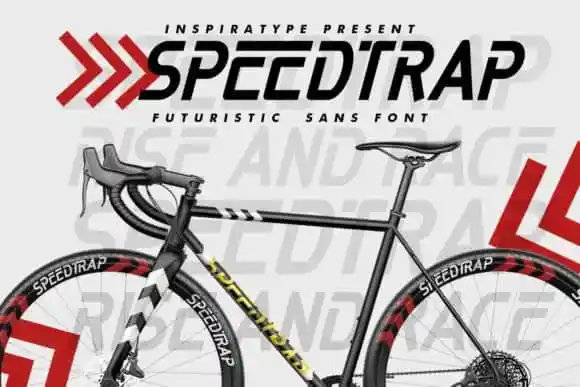
A Speedtrap Display Font é uma elegante fonte de display sans-serif que captura o espírito moderno do design atual. Ela transmite uma sensação alegre e fresca, combinando caracteres maiúsculos e minúsculos de maneira equilibrada e harmônica. A inspiração vem da Inspiratype Studio, designer responsável pela criação e disponibilização desta fonte impressionante. Com todas as versões dos caracteres incluídas – tanto maiúsculas quanto minúsculas, números e pontuação adicional – a Speedtrap oferece uma grande variedade de personalizações para o seu design. Além disso, ela também traz alternativas do OpenType e ligaturas comuns, além das tradicionais abordagens, que fornecem um conjunto completo de recursos. As opções mais elaboradas incluem swashes para cada caractere, permitindo uma variedade ilimitada de personalizações. A Speedtrap Display Font é perfeita tanto para logotipos quanto para criação de cartazes e materiais promocionais, como etiquetas ou design para roupas – oferecendo a capacidade de transformar qualquer projeto em algo realmente único e impecável.